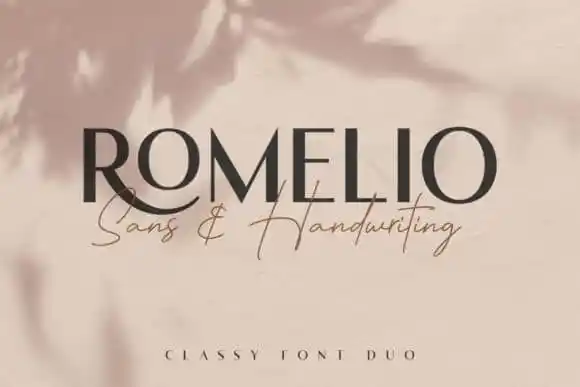
Romelio Sans Serif Font – Fonte Grátis
Romelio Sans Serif Font – Download Grátis
Romelio Sans Serif Font
Romelio Sans Serif é uma família de letras sem serif que enriquece com formas de letra simples, clássicas e elegantes. Esta fonte foi criada por Arterfak e disponibilizada para download na 99designs. Romelio não apenas oferece um estilo versátil e atraente, mas também eleva projetos gráficos ao topo da qualidade. Se você está procurando uma maneira de dar vida aos seus projetos criativos, este é o momento certo para adicionar Romelio à sua seleção de fontes favoritas. Suavemente modulada e facilmente adaptável, Romelio se ajusta perfeitamente a um amplo espectro de aplicações gráficas. Experimente incorporá-la em seu próximo design e veja o impacto real que ela pode fazer.